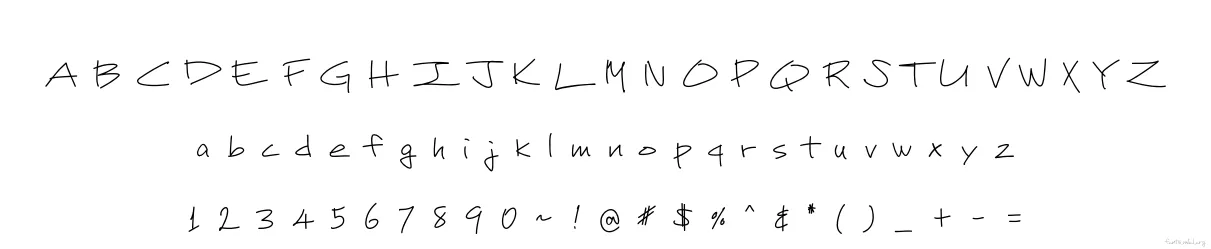
#1Ichiro 字体下载
字体名称:#1Ichiro
**Ichiro 字体下载指南**
Ichiro 是一款风格独特的字体,以其现代感和艺术性受到设计师的青睐。其流畅的线条和均衡的结构使其适用于多种设计场景,如海报、品牌标识和社交媒体内容。
这款字体尤其适合需要突出视觉冲击力的项目,搭配简约设计更能展现其魅力。无论是标题还是短文本,Ichiro 都能为作品增添个性。记得在使用时注意版权声明,尊重设计师的劳动成果。